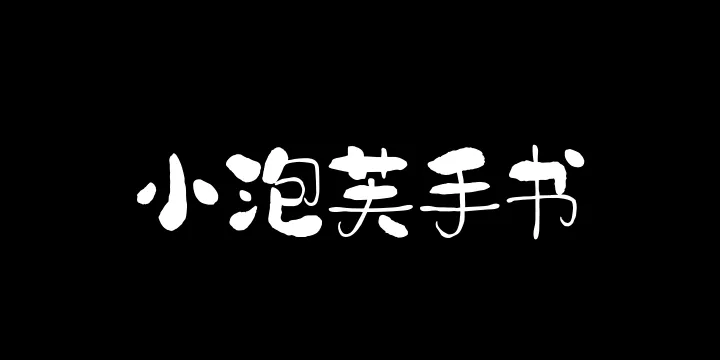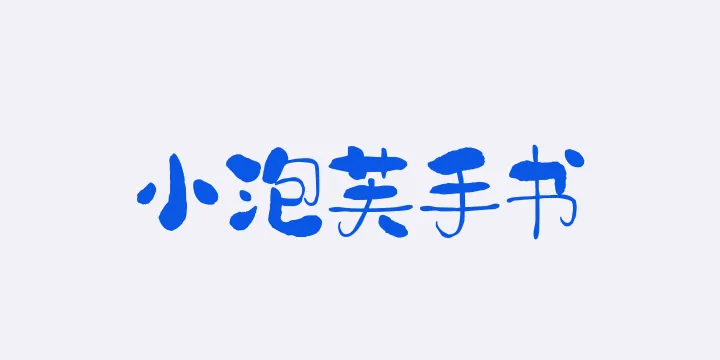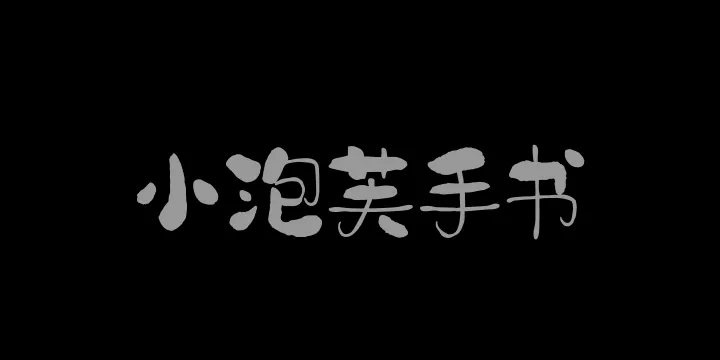
山海小泡芙手书W By 山海字库 商用字体
字体全名: 山海小泡芙手书W
字体简介: 山海小泡芙手书,是一款全新的卡通风毛笔字体,包含汉字9169个,符号200+个。该字体童趣可爱,结构多变灵动,笔画粗细对比强烈,字形活泼清新,造型生动有趣,具有灵活的适用性,天真俏皮又不失时尚感;同时以毛笔风格的表现形式,使字体更别具一格,笔画间的关系密不可分,同时也增加了字体的自由俏皮之感。